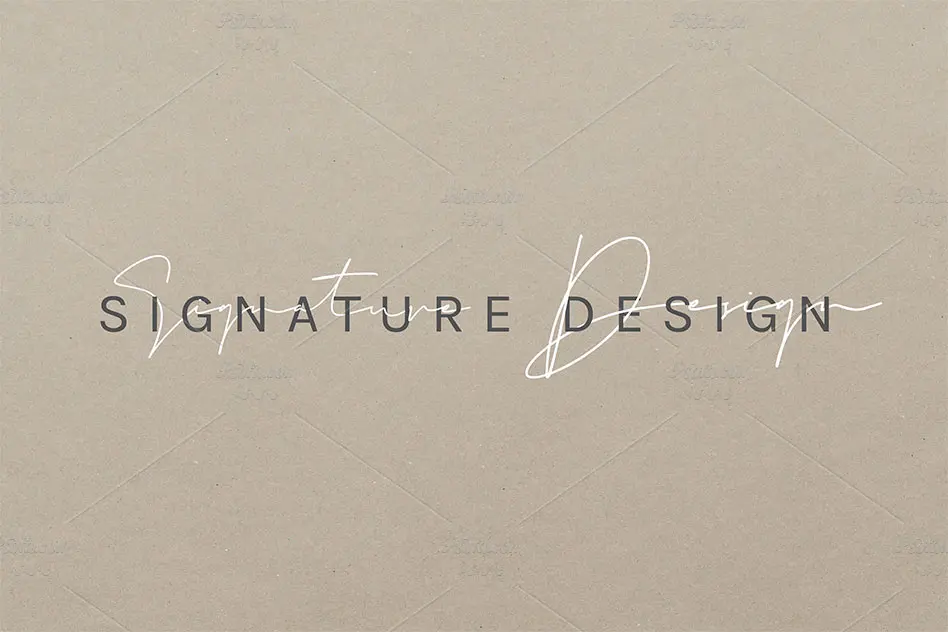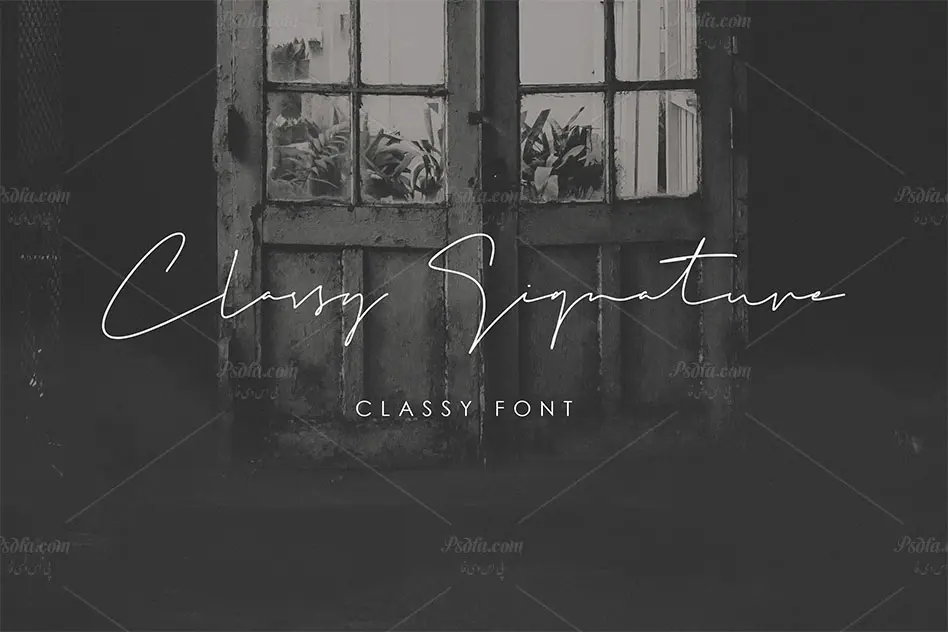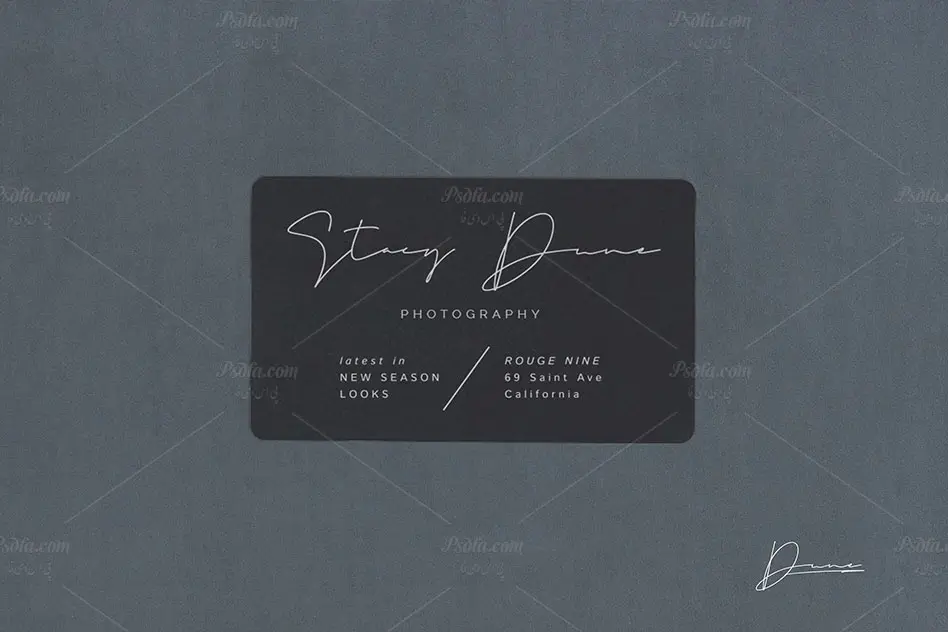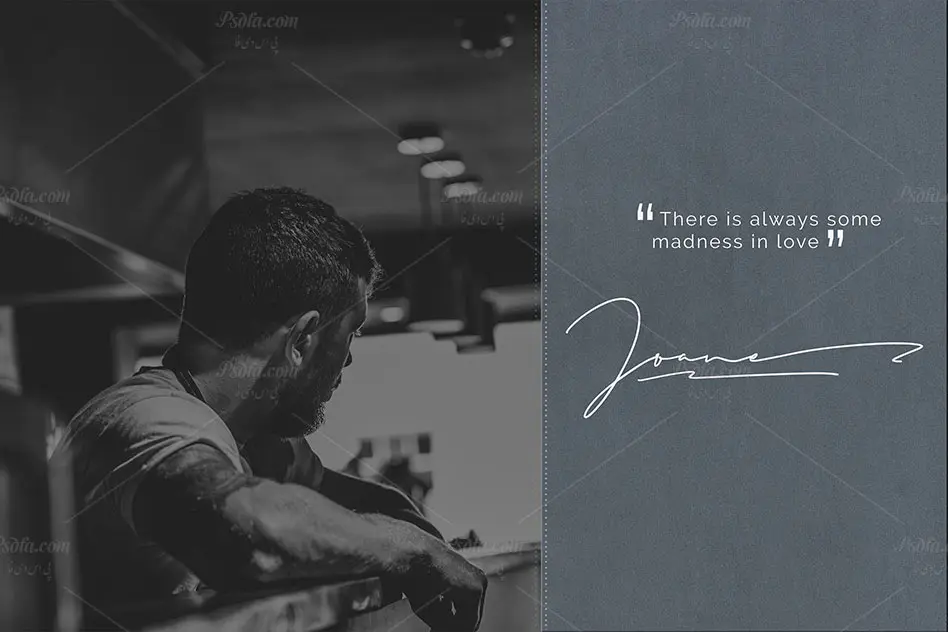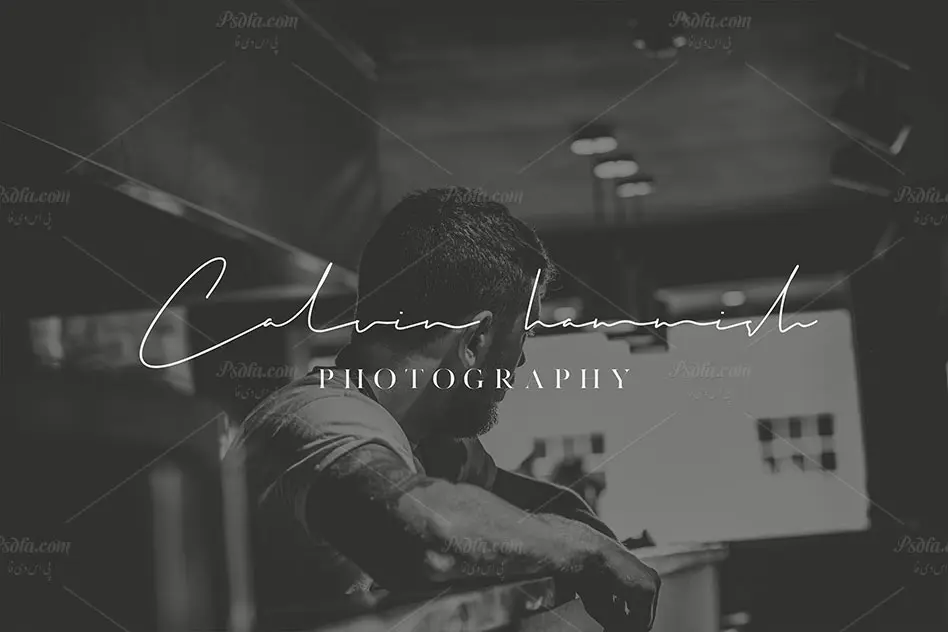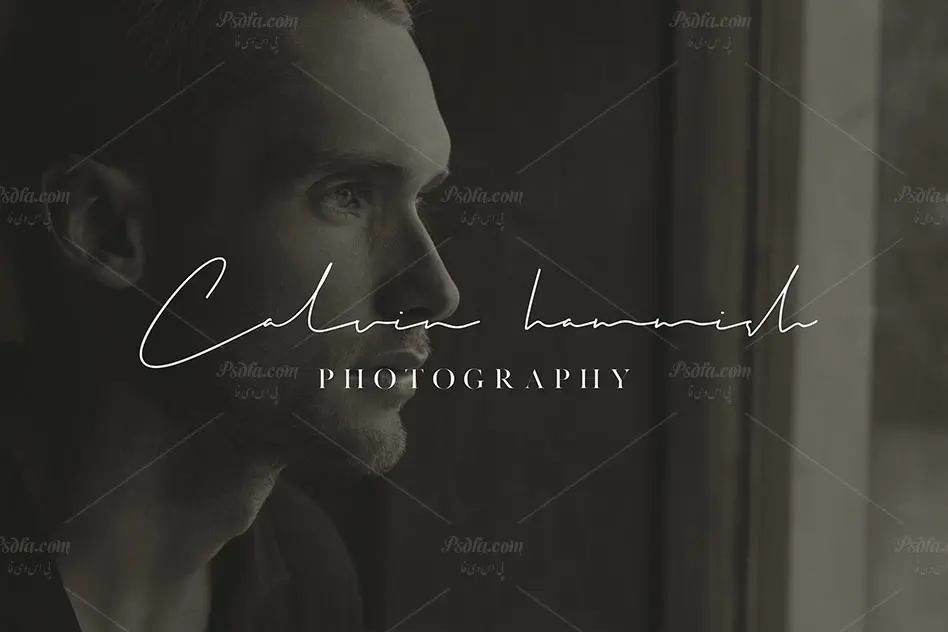
در این پست شاهد فونت انگلیسی امضا و دستنویس Raguel مناسب جهت استفاده در طراحی و گرافیک می باشید. این فونت فوق العاده زیبا در قالب 2 فایل ttf و otf در سایت بارگذاری شده اند که با نصب یکی از این دو فرمت در پوشه فونت های سیستم قادر به استفاده از آن در تمام نرم افزارهای گرافیکی و ویرایشگر متن از جمله نرم افزار محبوب فتوشاپ ، افتر افکت ، پریمیر ، مجموعه نرم افزار آفیس و … خواهید بود. فونت Raguel در وزن معمولی (Regular) طراحی شده است که از آن می توان در طرح های گرافیکی همچون طراحی انواع لوگو ، نام های تجاری ، طراحی کاور کتاب و مجله ، طراحی پوستر ، طراحی بسته بندی محصولات ، طراحی سایت ، کارت ویزیت ، تراکت ، بروشور و … استفاده نمود.
- نام فونت : Raguel
- وزن : معمولی (Regular)